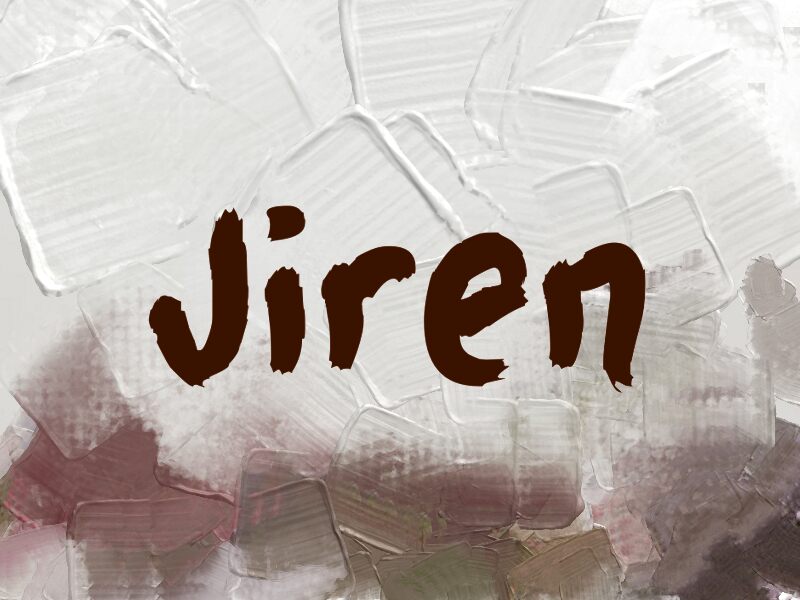
Jiren от Wep — это бесплатный кистевой шрифт с ярким, «рукописным» характером. Буквы выглядят так, будто их нанесли на бумагу щедрым мазком кисти, что придает формам плотные, неровные края и легкий, непринужденный ритм — это выглядит живо и аутентично, а не выглаженно.
Шрифт отлично подходит для плакатов, оформления музыкальных релизов, упаковки, айдентики кофеен и коротких заголовков в соцсетях, где нужно передать ощущение чего-то «сырого» и настоящего. Как бесплатный шрифт, Jiren также прекрасно работает в заголовках и на обложках, так как широкие, грубые штрихи придают динамичный и прямой вид даже коротким словам.
Jiren
Презентация и наглядный образец шрифта Jiren